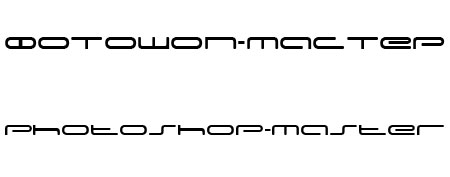
Дополнения Шрифты Татьяна Гапонова 7 июня 2009 Шрифт - DS Podd Cyr Необычный шрифт с поддержкой русского языка. Скачать Шрифт - DS Podd Cyr
красивый шрифт,я его искала *О*
"Квиксильвер" пишется именно таким шрифтом. Вроде